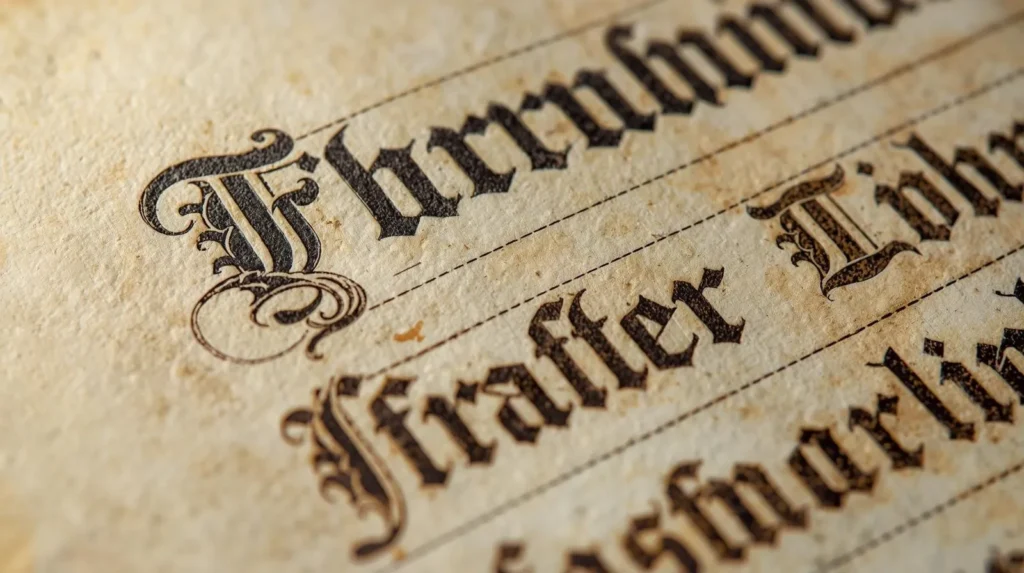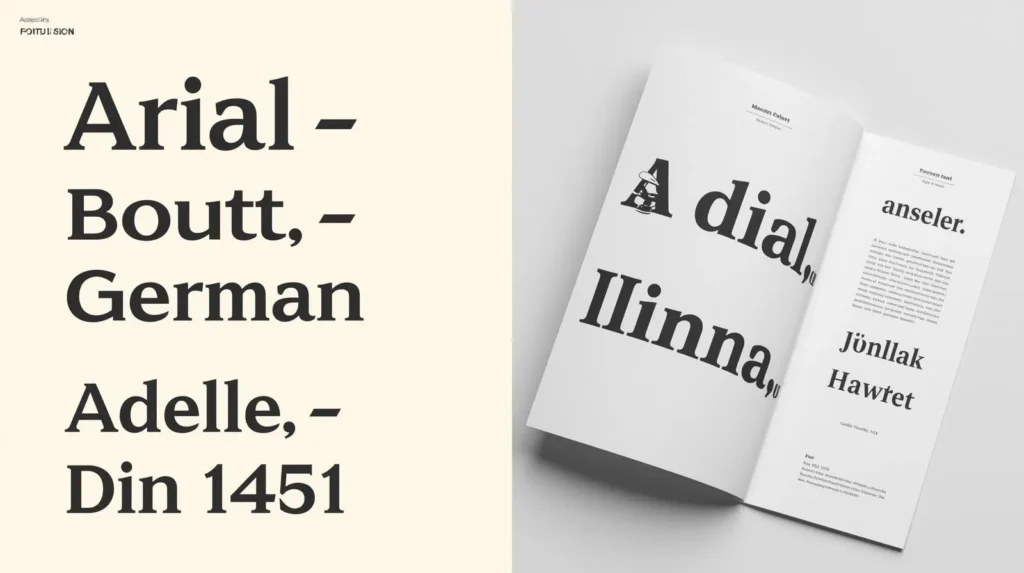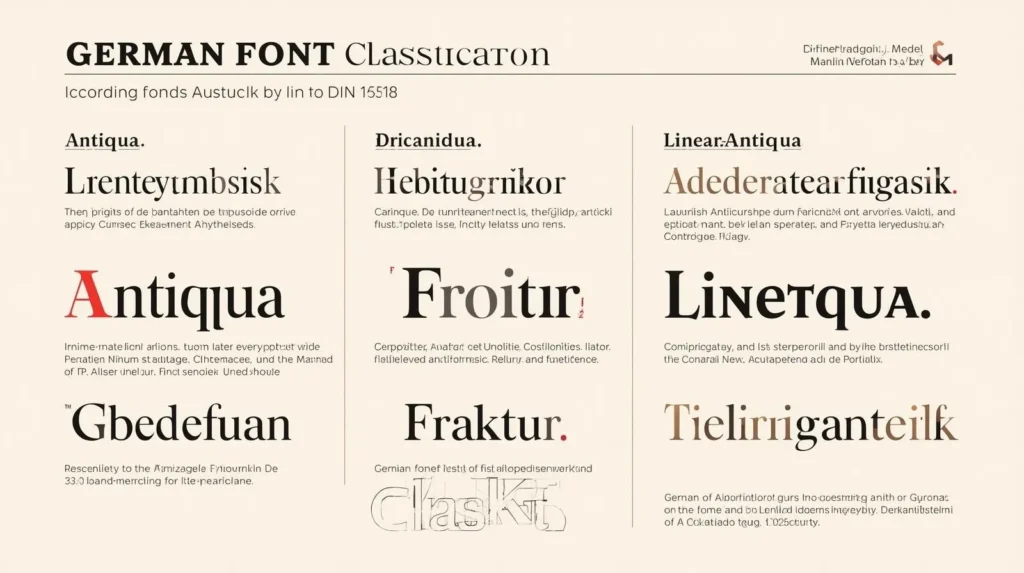
Welche Schriftarten gibt es in Deutschland – Beliebte Fonts
Deutschland hat eine lange und spannende Geschichte, wenn es um Schriftarten geht. Schon seit Jahrhunderten haben sich verschiedene Schriftstile entwickelt, die nicht nur funktional waren, sondern auch Kultur und Ästhetik widerspiegelten. Heute gibt es eine riesige Vielfalt – von alten, historischen Druckschriften bis zu modernen, klaren Fonts, die wir täglich auf Bildschirmen und in Printmedien sehen. Aber welche Schriftarten findet man in Deutschland eigentlich? Schauen wir uns das genauer an.
Historische deutsche Schriftarten
Früher waren gebrochene Schriften das A und O in Deutschland. Sie dominierten Bücher, offizielle Dokumente und sogar Briefe. Die bekanntesten Vertreter sind:
• Fraktur – Sie ist vielleicht die bekannteste „deutsche Schrift“. Mit ihren markanten, gebrochenen Linien war sie lange Zeit Standard in der Druckwelt.
• Schwabacher – Eine etwas weichere Variante der Fraktur, sehr beliebt im 15. und 16. Jahrhundert.
• Deutsche Kurrentschrift – Eine Handschrift-artige Schrift, die in Schulen gelehrt wurde. Ihre verschnörkelten Buchstaben wirken sehr charakteristisch.
• Sütterlinschrift – Abgeleitet von der Kurrentschrift und Anfang des 20. Jahrhunderts weit verbreitet. Heute sieht man sie vor allem in historischen Dokumenten oder als dekorativen Stil.
Diese alten Schriften wirken auf uns heute oft sehr kunstvoll, aber früher waren sie einfach Teil des Alltags. Viele Designer nutzen sie heute noch, um Projekten einen historischen oder eleganten Touch zu geben.
Moderne deutsche Schriftarten
Mit der Zeit kamen die modernen Schriftarten auf, die wir heute überall sehen:
• Serifen-Schriften (Antiqua): Dazu gehören klassische Fonts wie Adelle oder Barock-Antiqua. Sie wirken elegant und gut lesbar – perfekt für Bücher, Zeitschriften oder offizielle Texte.
• Serifenlose Schriften: Beispiele sind Arial, Akkurat oder Akzidenz Grotesk. Diese Fonts sind klar, neutral und besonders beliebt für Webseiten, Präsentationen oder Plakate.
• DIN-Schriften: Die DIN 1451 ist ein Standard für Verkehrsschilder, technische Dokumente und viele Behörden. Sie ist einfach, funktional und sehr klar zu lesen.
Heutzutage werden in Deutschland auch internationale Schriftarten viel genutzt. Gerade im digitalen Bereich greifen Designer gern auf klare, moderne Fonts zurück, die gut am Bildschirm lesbar sind.
Schriftklassifizierung in Deutschland
In Deutschland gibt es sogar offizielle Klassifizierungen für Schriftarten, die in DIN-Normen festgehalten sind. Nach DIN 16518 werden Schriften in insgesamt elf Klassen eingeteilt – von klassischen Antiqua-Schriften bis zu gebrochenen Schriften und Schreibschriften.
Ein paar Beispiele:
• Renaissance-Antiqua & Barock-Antiqua: Elegante Serifenschriften, oft für Bücher oder offizielle Dokumente.
• Serifenlose Linear-Antiqua: Klare, moderne Schriften, ideal für digitale Medien.
• Gebrochene Schriften: Historische Schriften wie Fraktur oder Schwabacher.
• Schreibschriften: Handschriftlich wirkende Fonts, z. B. Sütterlin oder moderne Handwriting-Fonts.
Diese Klassifizierung hilft nicht nur Designern, die passende Schrift zu wählen, sondern zeigt auch, wie vielfältig die deutsche Typografie ist. Je nach Projekt – ob digital, Print oder Werbung – kann man genau die richtige Schrift auswählen.
Bekannte Beispiele deutscher Schriftarten
Hier sind einige bekannte Schriften, die man in Deutschland häufig findet:
Historisch:
• Schwaben Alt – klassisch gebrochen
• Blackletter Hand – dekorativ, traditionell
• Edda – elegante alte Schrift
• Herzog Von Graf – auffällig und charakterstark
Modern:
• Helvetica – neutral, modern, sehr beliebt
• Adelle – serifenschön, gut lesbar
• Arial – klar und vielseitig
• Akkurat – minimalistisch, digital-geeignet
Jede dieser Schriften hat ihren eigenen Charakter. Historische Fonts geben Projekten einen klassischen, traditionellen Look, während moderne Fonts klar, neutral und vielseitig sind.
Fazit
Deutschland bietet eine riesige Auswahl an Schriftarten, von kunstvollen historischen Schriften bis zu modernen, digitalen Fonts. Die Wahl hängt immer vom Zweck und Stil des Projekts ab:
• Für einen historischen oder eleganten Touch: Fraktur, Schwabacher oder Sütterlin.
• Für digitale Medien oder Print: Serifenlose und serifenbetonte moderne Fonts wie Arial, Helvetica oder Adelle.
Wer die Vielfalt kennt, kann seine Projekte genau so gestalten, dass sie ästhetisch wirken und gut lesbar sind – und dabei auch ein Stück deutscher Typografie-Geschichte transportieren.